Bạn đã bao giờ dành hàng giờ đồng hồ lướt mạng tìm một kiểu chữ hoài cổ ưng ý, nhưng đến khi gõ tiếng Việt thì dấu ngã, dấu hỏi lại “nhảy” thành những ô vuông lỗi nhàm chán? Chúng tôi hoàn toàn thấu hiểu sự ức chế đó của các designer khi phải xử lý những font chữ không hỗ trợ tiếng mẹ đẻ.
Đồng hành cùng bạn, chúng ta sẽ lần lượt giải mã sức hút của phong cách Typography này, cách ứng dụng thực chiến vào các ấn phẩm thiết kế nghệ thuật, và dĩ nhiên là trọn bộ link tải chất lượng nhất dành riêng cho bạn.
Font chữ Retro là gì?
Trước khi trực tiếp tải xuống bộ sưu tập, chúng tôi muốn bạn nắm rõ bản chất cốt lõi của phong cách typography này. Font chữ Retro là thuật ngữ chỉ các bộ phông mô phỏng lại những trào lưu thị giác rực rỡ trong giai đoạn từ thập niên 60s đến 90s.
Thay vì chạy theo sự mượt mà tuyệt đối của thời đại số, thiết kế chữ hoài cổ sở hữu một ngôn ngữ tạo hình hoàn toàn khác biệt và đậm chất thủ công:
- Đường nét: Thường là các nét bo tròn phồng rộp mang âm hưởng Pop-Art vui nhộn, hoặc vát nhọn sắc sảo của các biển hiệu quảng cáo vẽ tay xưa cũ.
- Hiệu ứng bề mặt: Đi kèm với kết cấu xước mộc mạc, nhiễu hạt (noise) và bóng đổ khối lập thể để tạo độ sâu ấn tượng.
Tại sao xu hướng này lại trỗi dậy mạnh mẽ giữa nhịp sống hiện đại? Bí quyết cạnh tranh nằm ở khả năng chạm vào tâm lý hoài niệm (nostalgia). Khi thị giác người dùng bị bão hòa bởi các thiết kế phẳng lỳ và rập khuôn, một phông chữ nhuốm màu thời gian sẽ ngay lập tức tạo ra sự kết nối cảm xúc, mang lại cảm giác ấm áp và đáng tin cậy.
Sự giao thoa tinh tế giữa nét cổ điển và tư duy sắp chữ đương đại đang thực sự tỏa sáng trong các ấn phẩm truyền thông nghệ thuật. Hãy tưởng tượng bạn đang dàn trang catalogue giới thiệu tác phẩm cho một không gian trưng bày cao cấp như Artnam Gallery.
Việc ứng dụng một phông chữ retro có chân được căn chỉnh tracking tỉ mỉ, đặt cạnh hình ảnh những bức tranh sơn mài hay tranh sơn dầu đậm tính truyền thống sẽ lập tức tạo ra chiều sâu văn hóa. Con chữ lúc này vượt qua chức năng đọc hiểu thông thường, chúng trở thành một phần của tác phẩm và dẫn dắt người xem đắm chìm vào câu chuyện di sản đầy tự hào.
Top 34+ font retro được sử dụng nhiều nhất trong thiết kế
Font retro là lựa chọn quen thuộc trong các thiết kế cần tạo cảm giác hoài cổ, nổi bật và giàu cá tính. Tùy theo phong cách thương hiệu, bạn có thể chọn font retro kiểu disco 70s, vintage serif, script cổ điển, Art Deco hoặc font thời bao cấp Việt hóa.
Dưới đây là danh sách hơn 25 font retro được sử dụng phổ biến trong thiết kế bao bì, poster, logo, menu, nhãn sản phẩm và ấn phẩm truyền thông.
1. Pacifico
Pacifico là font script mang phong cách surf retro thập niên 60–70. Nét chữ mềm, phóng khoáng, phù hợp với logo quán cà phê, bao bì đồ uống, beach bar, tiệm bánh hoặc các thiết kế mang tinh thần California vintage.
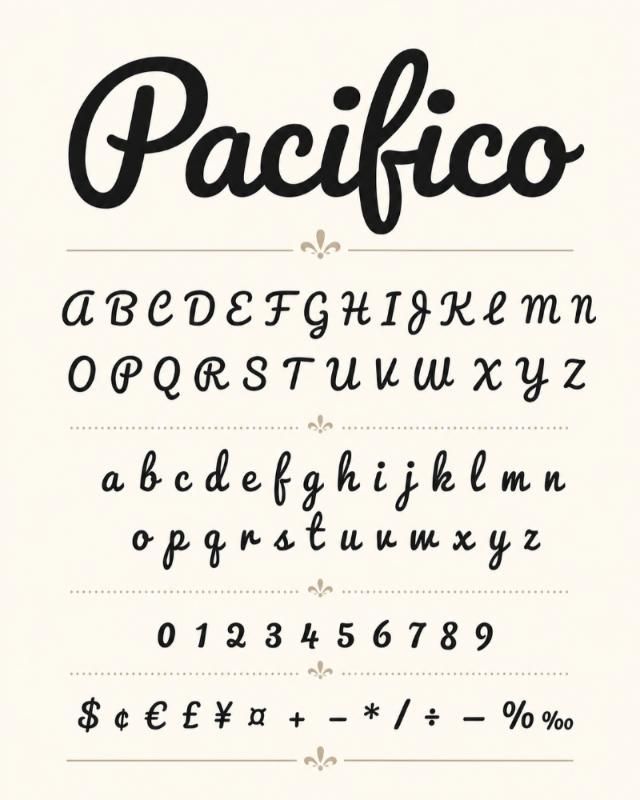
2. Righteous
Righteous có nét chữ đậm, chắc và hơi hướng groovy 70s. Font này thường được dùng cho poster âm nhạc, banner sự kiện, bao bì thực phẩm retro hoặc các thiết kế cần cảm giác vui nhộn, mạnh mẽ.
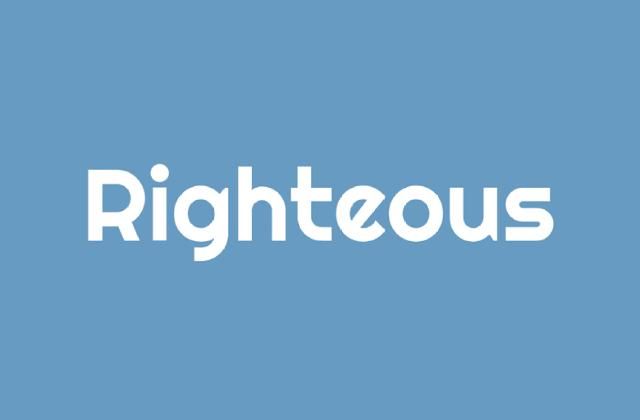
3. Bungee
Bungee là font retro signage đậm chất biển hiệu Mỹ thập niên 70. Kiểu chữ dày, nổi bật, dễ tạo điểm nhấn trên poster quảng cáo, standee sự kiện, tiêu đề lớn hoặc bao bì cần khả năng nhận diện cao.
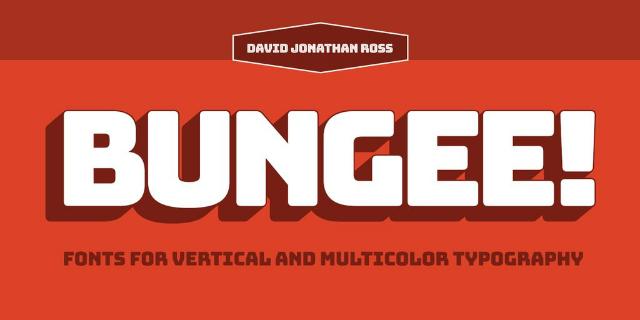
4. Fredoka One
Fredoka One có dáng chữ bo tròn, mềm và vui tươi. Font phù hợp với bao bì snack, đồ ngọt, sản phẩm trẻ em, poster hoạt hình hoặc thiết kế cần cảm giác thân thiện, trẻ trung.
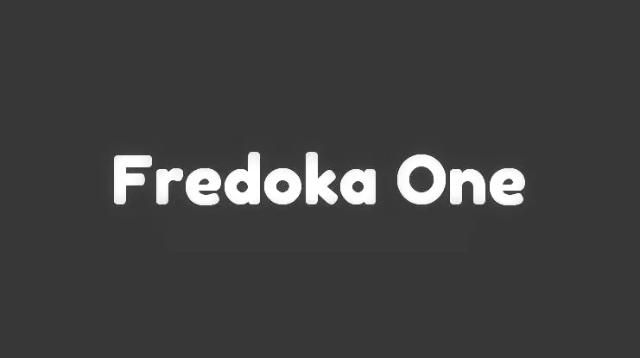
5. Shrikhand
Shrikhand là font display có phong cách retro pha trộn giữa nét Ấn Độ và phương Tây. Font tạo cảm giác lạ mắt, phù hợp với tiêu đề, poster nghệ thuật, bao bì sản phẩm thủ công hoặc thương hiệu muốn có cá tính riêng.
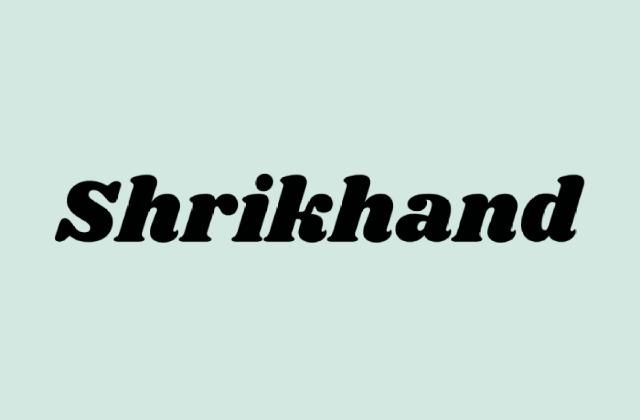
6. Lobster
Lobster là font script retro rất phổ biến, gợi nhớ phong cách biển hiệu cũ thập niên 50. Font hợp với menu nhà hàng vintage, logo diner, quán cà phê, nhãn đồ uống hoặc các thiết kế cần nét mềm mại nhưng vẫn nổi bật.
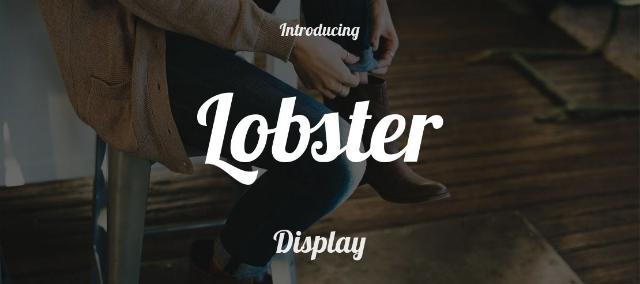
7. Cookie
Cookie có nét chữ script nhẹ nhàng, thanh lịch và dễ đọc. Font phù hợp với thiệp mời, nhãn handmade, bao bì mỹ phẩm, tiệm bánh hoặc các thiết kế vintage nữ tính.
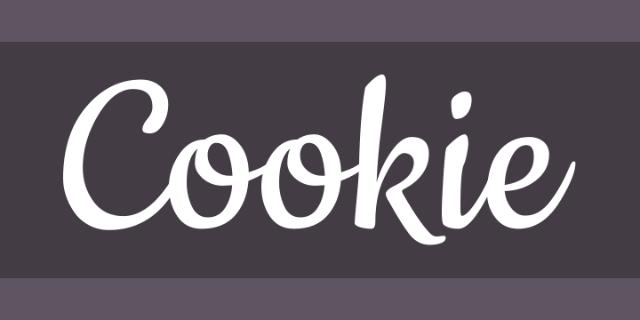
8. Sacramento
Sacramento mang phong cách chữ viết tay liền mạch, cổ điển thập niên 40–50. Font thường dùng cho thiệp cưới vintage, nhãn sản phẩm thủ công, poster nhẹ nhàng hoặc thương hiệu cần cảm giác tinh tế.
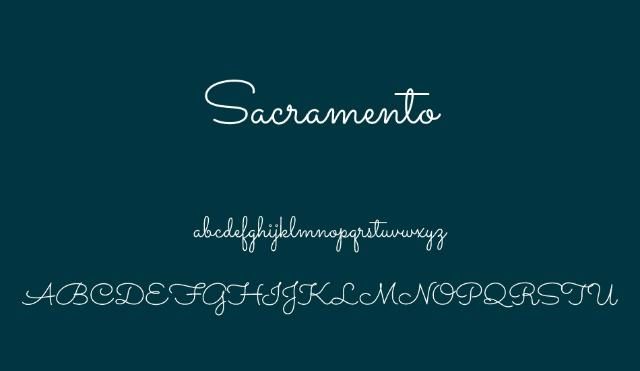
9. Allura
Allura là font script trang nhã, có nét thư pháp vintage. Font phù hợp với thương hiệu làm đẹp, thiệp mời, bao bì cao cấp, quà tặng hoặc các thiết kế cần sự mềm mại và sang trọng.
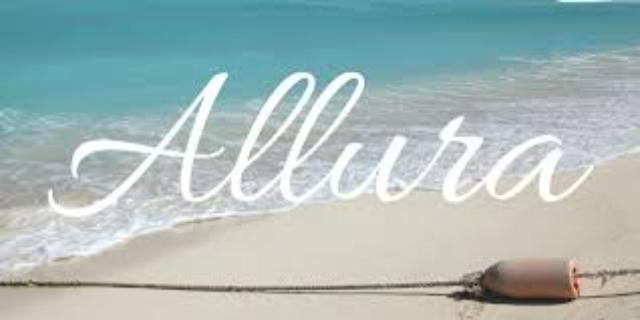
10. Great Vibes
Great Vibes có dáng chữ cursive cổ điển, uyển chuyển và giàu cảm xúc. Đây là lựa chọn tốt cho logo thời trang, thiệp cưới, bìa sách, nhãn sản phẩm cao cấp hoặc thiết kế mang tinh thần lãng mạn.
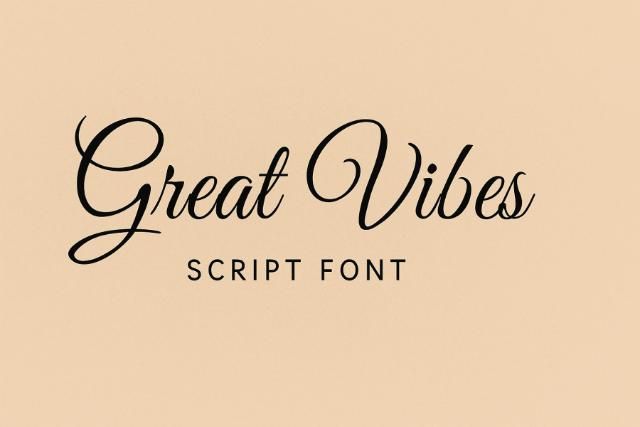
Font retro nào phù hợp nhất để thiết kế catalogue mỹ thuật/triển lãm? Đối với các không gian trưng bày nghệ thuật, nhóm font Retro Serif là chân ái. Những cái tên như Classico hay Losta Masta với nét sắc sảo sẽ làm tôn lên vẻ đẹp của tranh sơn mài hay nghệ thuật đương đại mà không làm lu mờ tác phẩm chính.
Cách tìm font retro chuẩn trên Canva? Rất đơn giản, tại thanh tìm kiếm font chữ của Canva, bạn chỉ cần gõ các từ khóa như: vintage, retro, nostalgia, 70s hoặc typewriter. Canva sẽ tự động lọc ra các kiểu chữ mang phong cách hoài cổ đang có sẵn trong kho dữ liệu của họ.